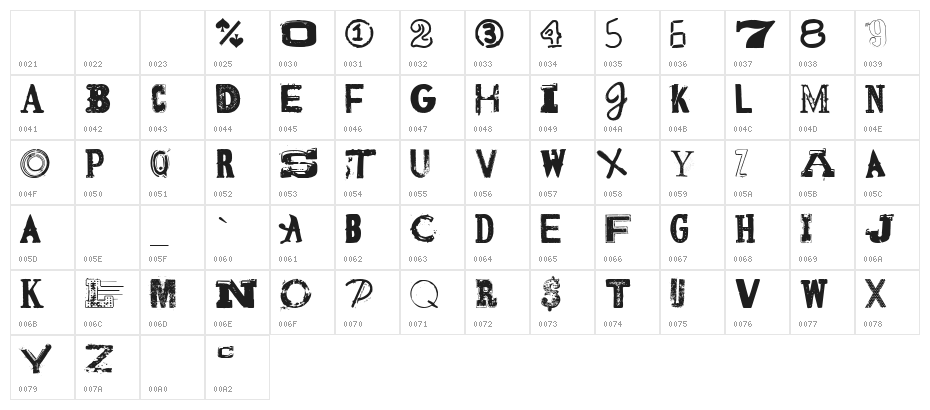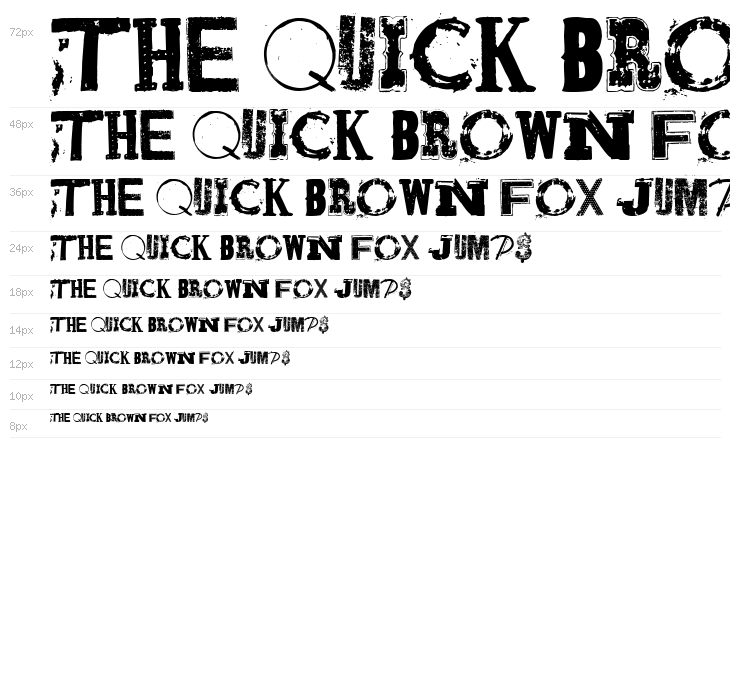
Jailbox1 Font
| Stile generale | Vintage, Grunge |
| Progetti proposti | Ideal for posters, album covers, branding for edgy or alternative products, and any design needing a bold, distressed look. |